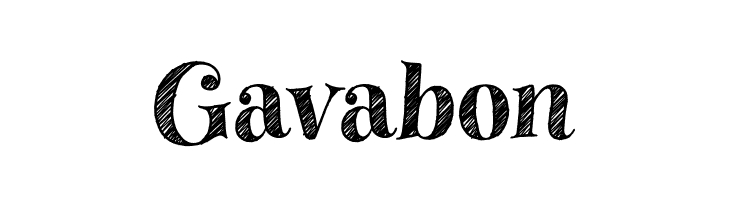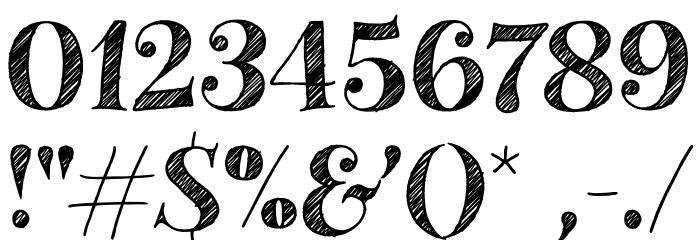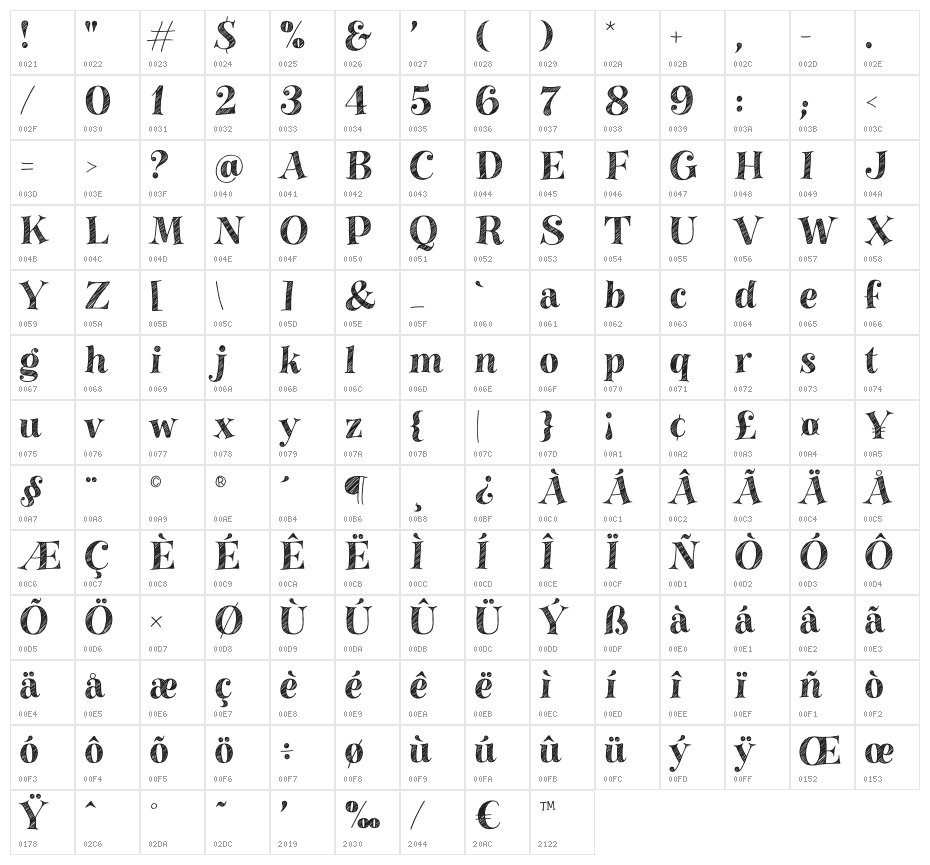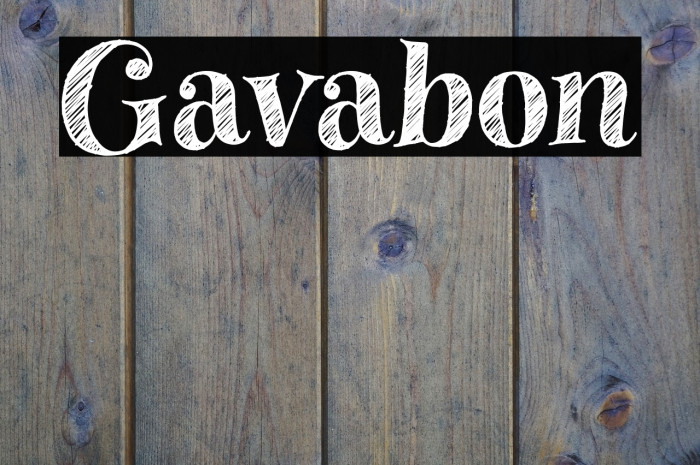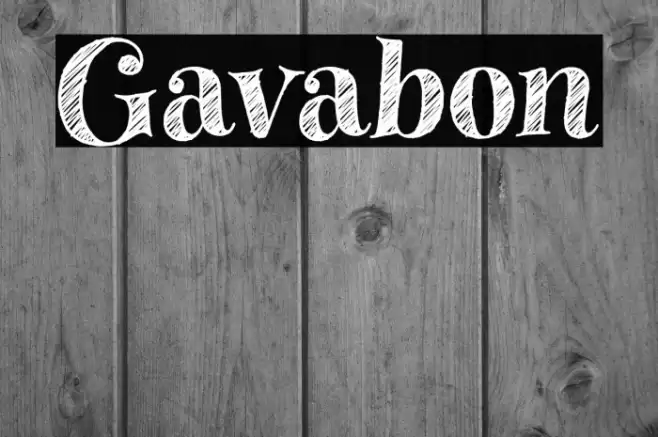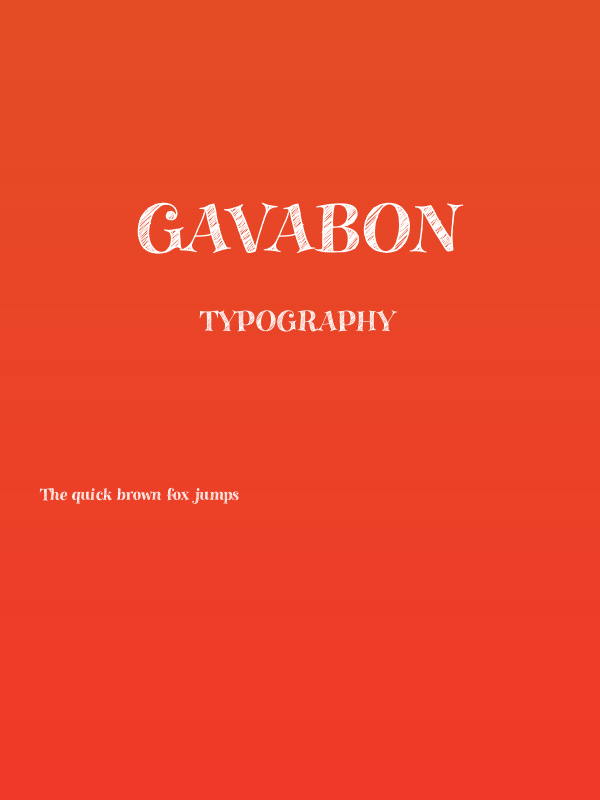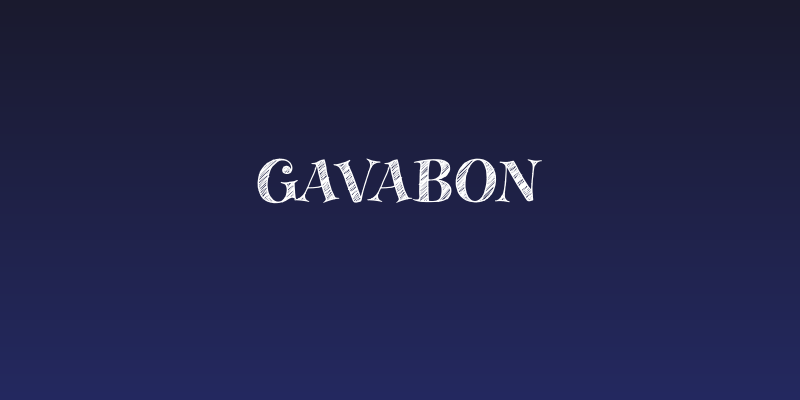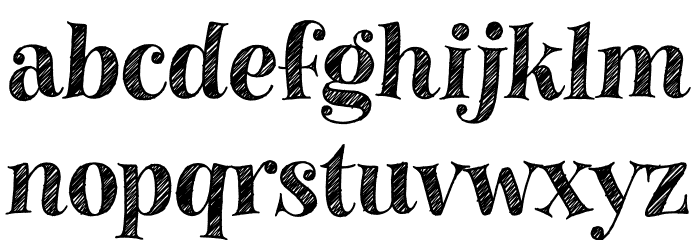
Gavabon Font
| Proiecte propuse | Ideal for creative projects such as posters, branding, packaging, and headlines where a bold and artistic touch is desired. |